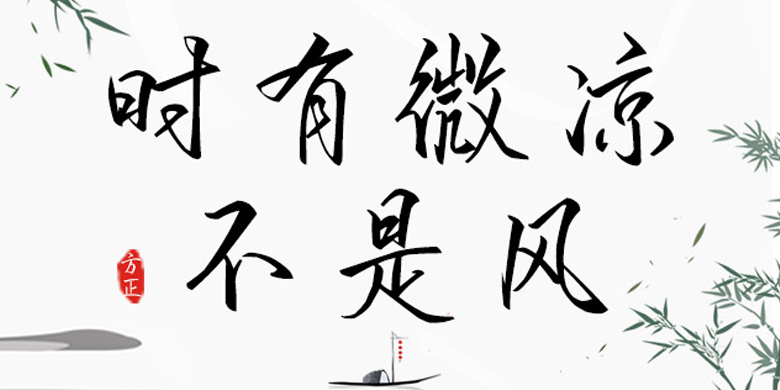
方正手迹-时有微凉不是风
字体品牌: 方正手迹 设计师:余丹 字体分类:创意书写 字体属性:精品字 字符集:简繁扩展(GBK) 发布时间: 2020
时有微凉不是风这款字体用笔潇洒从容,粗细变化,自然随意,重心平稳,韵味悠长。适用于文艺类的书刊、文化类宣传设计、综艺字幕、品牌广告和产品包装设计,以及社交网络的个性化用字。